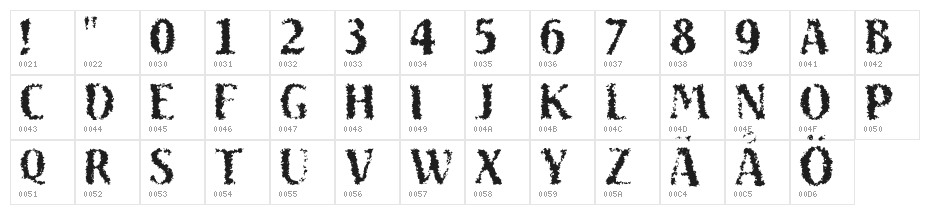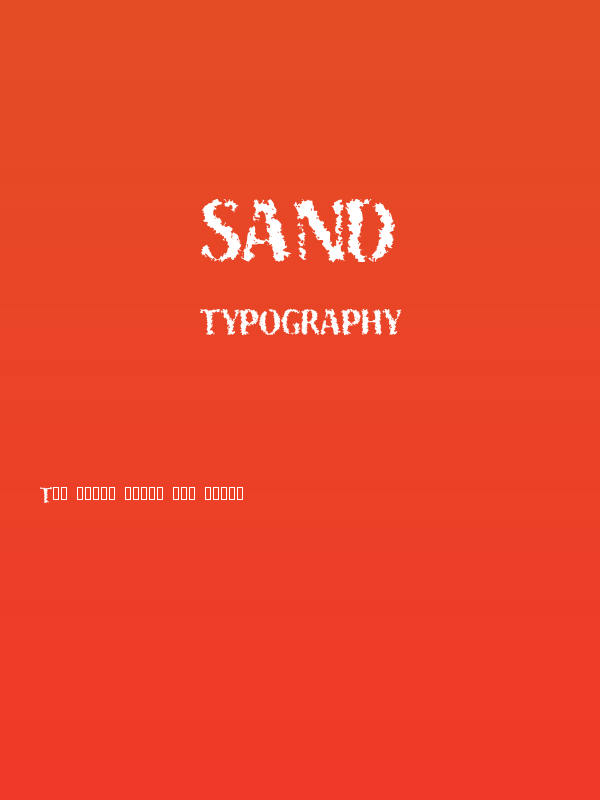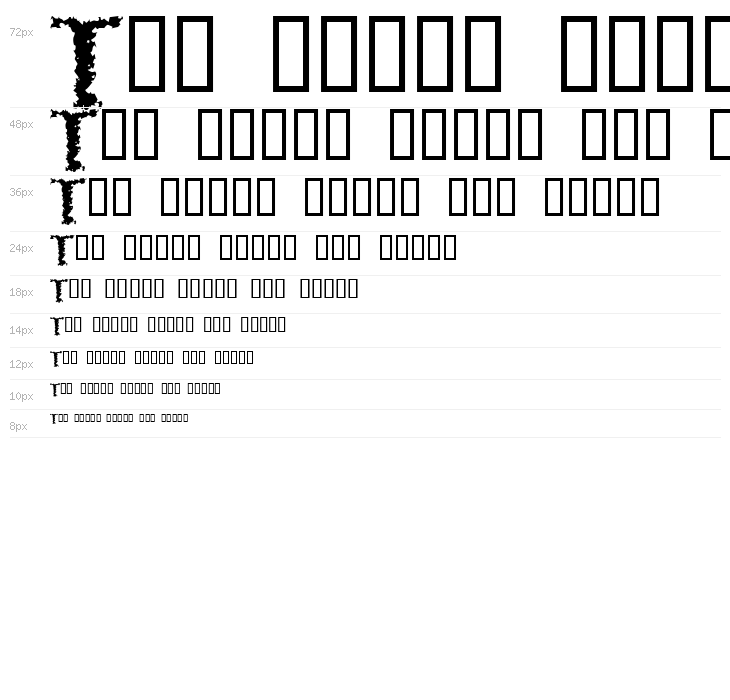
Sand Font
| 分类 | Capitals |
| 推荐项目 | Ideal for nature-themed designs, outdoor event posters, rustic branding, or any project needing a textured, organic look. |